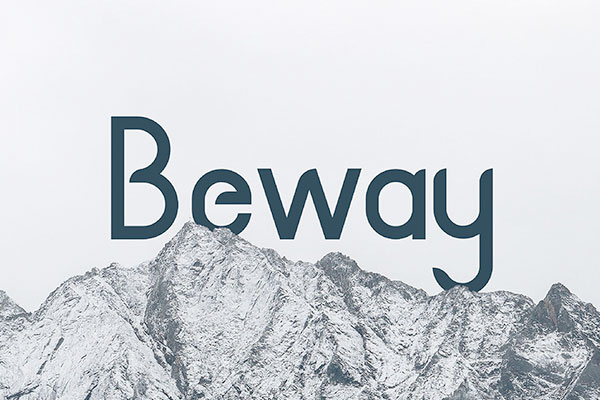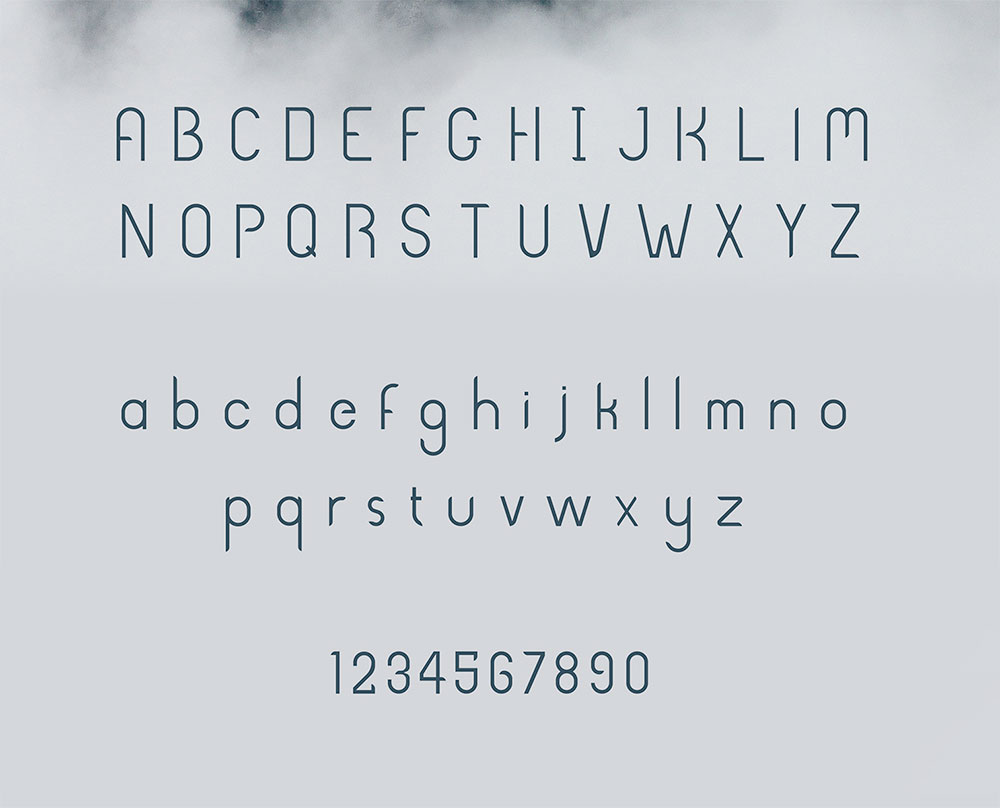
BEWAY字体
Beway是一款由设计师Azer Nesib倾心打造的英文字体,于Behance首次亮相,并由作者亲自声明,可用于个人和商业用途,完全免费。
这款字体包含了两种字重,除了您在图片中已见到的常规版本外,还有一个轻盈灵动的细体版本。为了让您更方便地使用这款字体,本站已经将两种版本一并打包整理,供您下载。